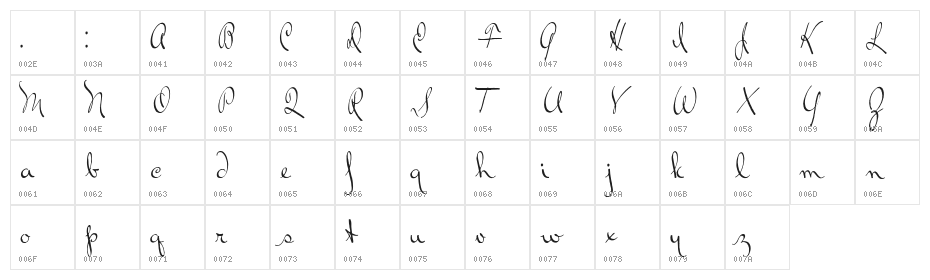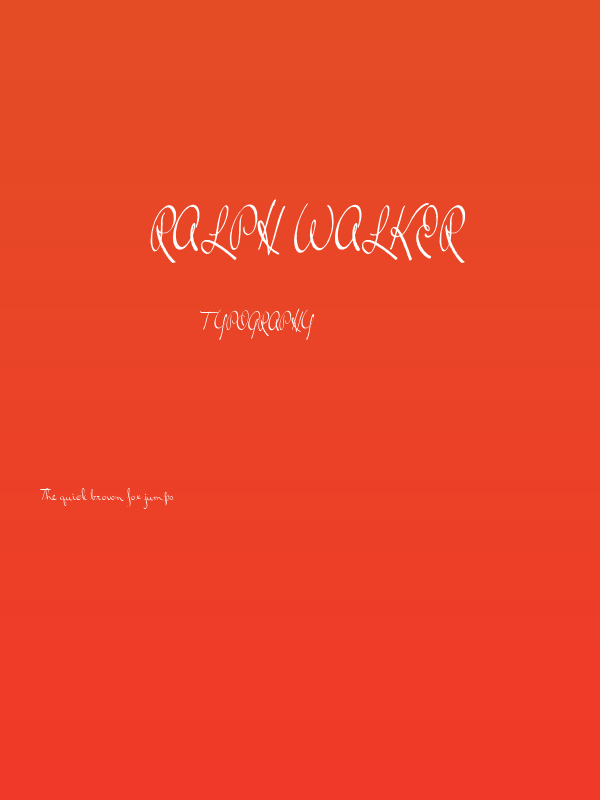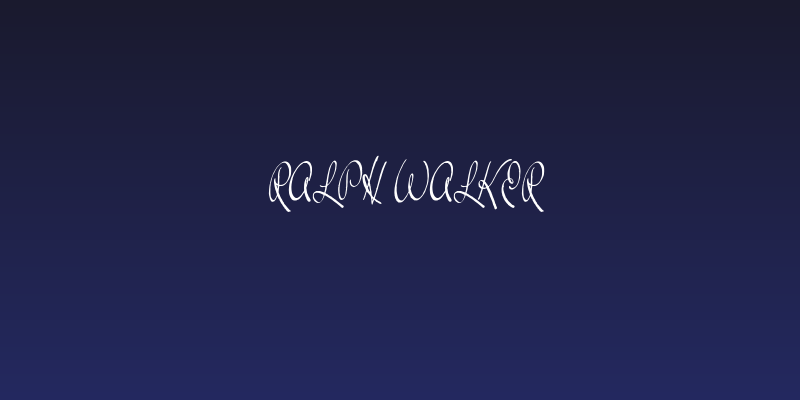
Ralph Walker Font
| Caso d'uso | Logos, Invitations, Artistic projects |
| Progetti proposti | Ideal for wedding invitations, greeting cards, personal branding, and artistic projects. |